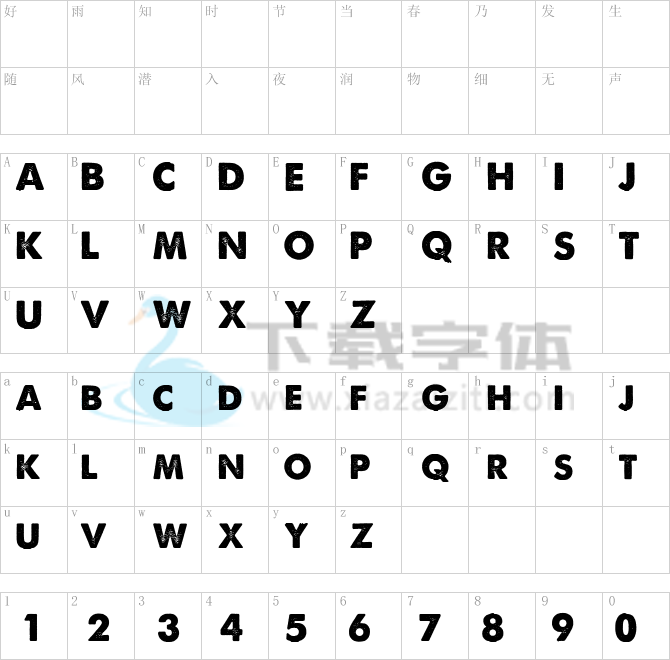
A Love of Thunder.ttf字体下载
A Love of Thunder.ttf字体下载,这款字体结构工整、笔画清晰,兼顾美观与易读性,适用于标题、正文、海报、包装、LOGO 等多种场景。字形优雅稳定,风格百搭耐看,适配日常排版与创意设计,让文字呈现更舒适、更具质感。A Love of Thunder.ttf字体下载一笔一画,皆是细节,以均衡的比例、流畅的线条打造舒适视觉体验,字形端正大气,风格简约现代。无论是商业设计、品牌宣传还是日常排版,都能轻松驾驭,让文字更有格调与力量。A Love of Thunder.ttf字体下载字体下载。